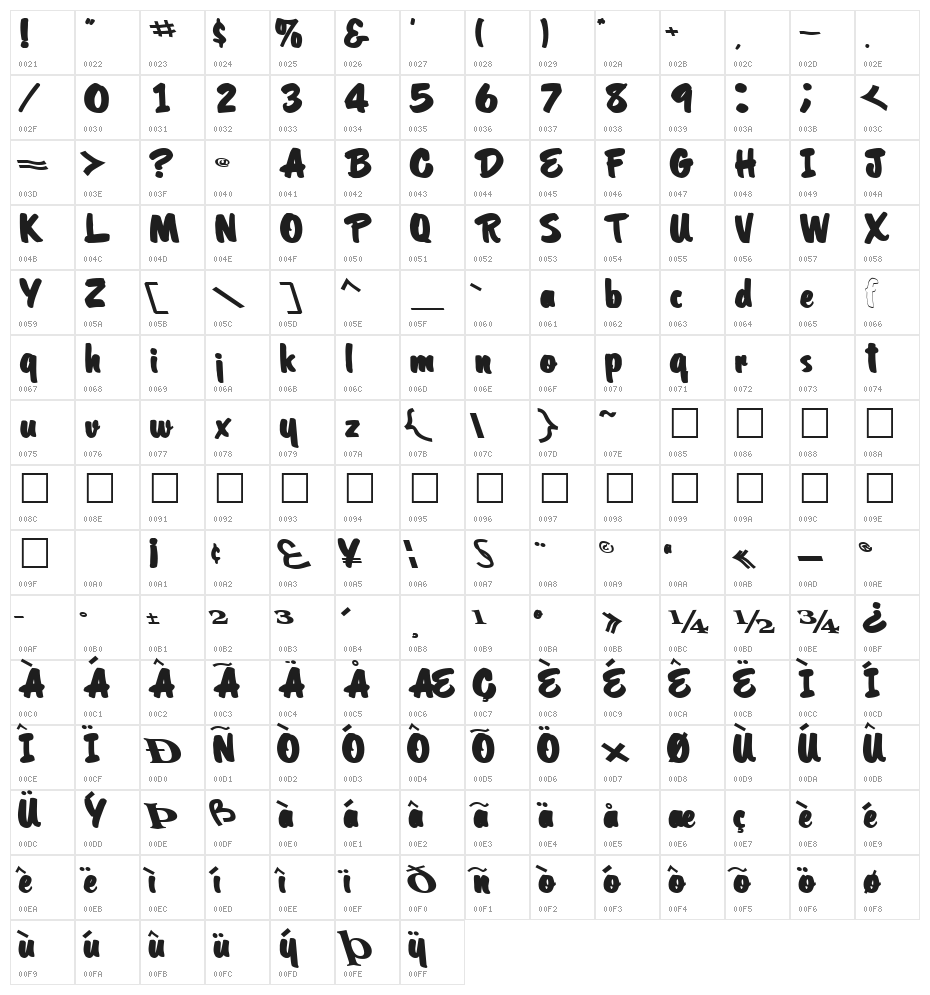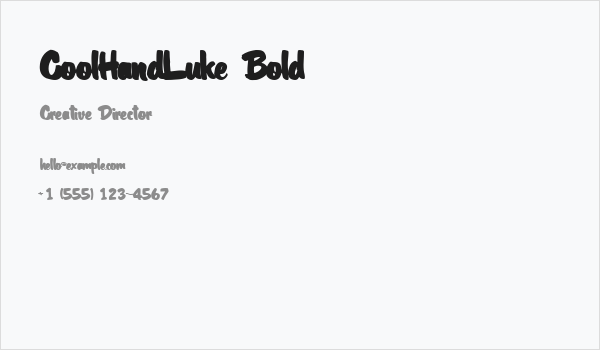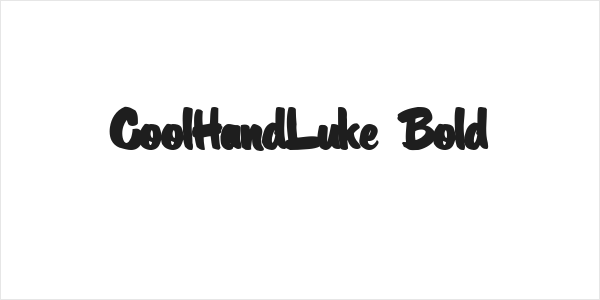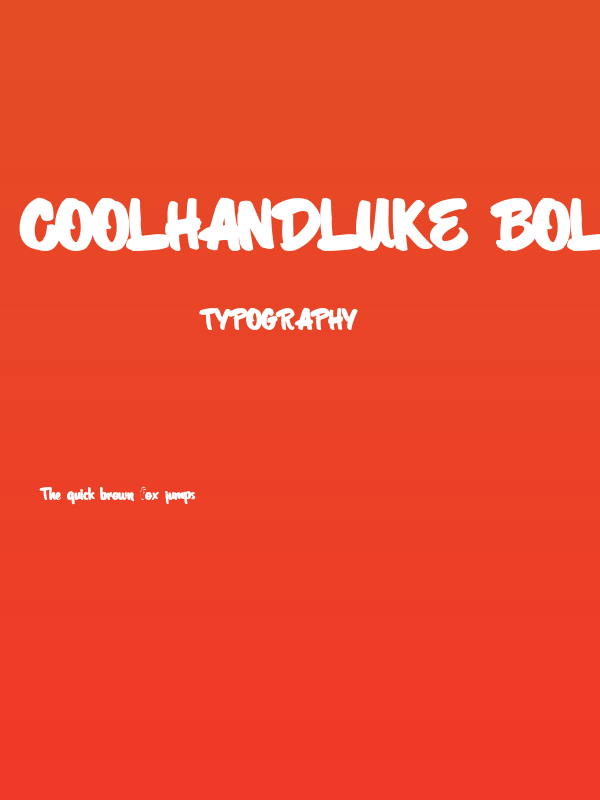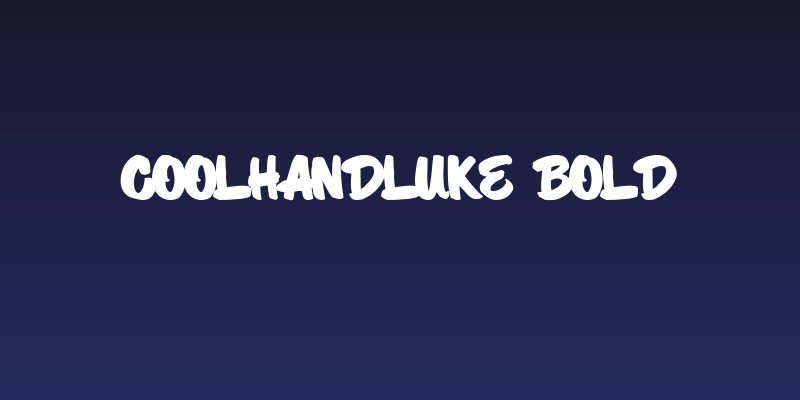
CoolHandLuke Bold Font
| Estilo general | Playful |
| Caso de uso | Logos, Headlines, Posters |
| Proyectos propuestos | Perfect for children's books, playful branding, casual invitations, and creative posters. |